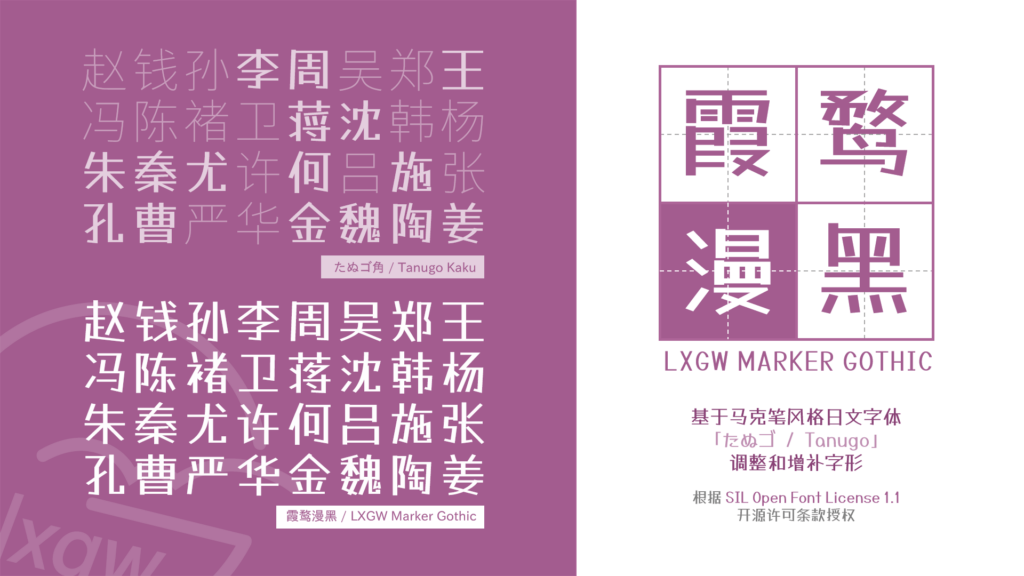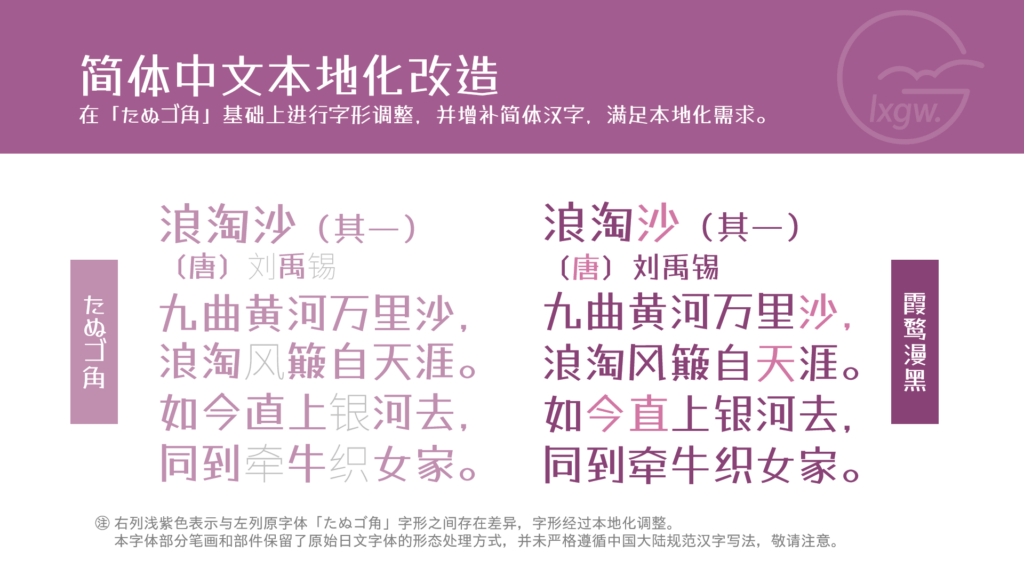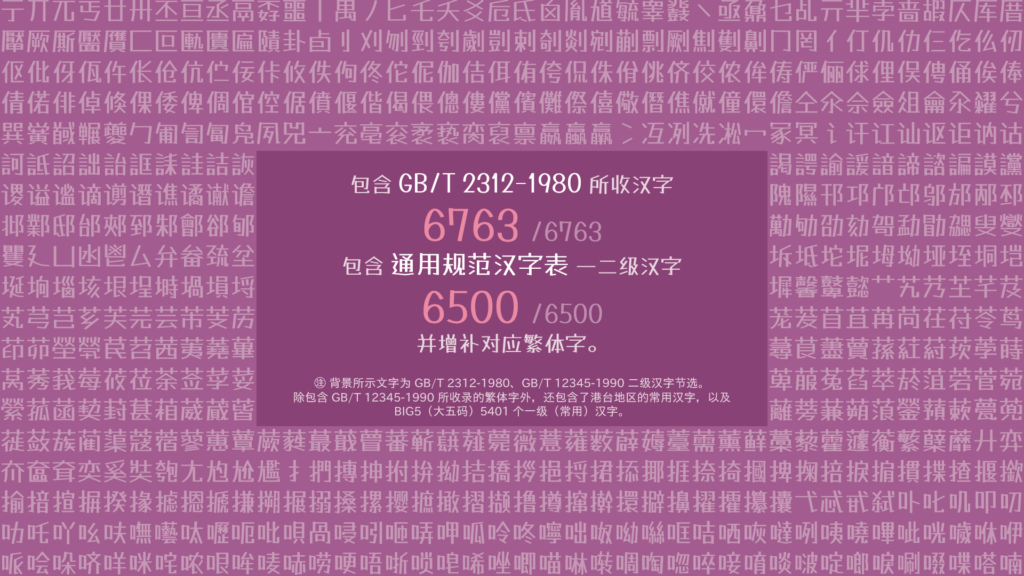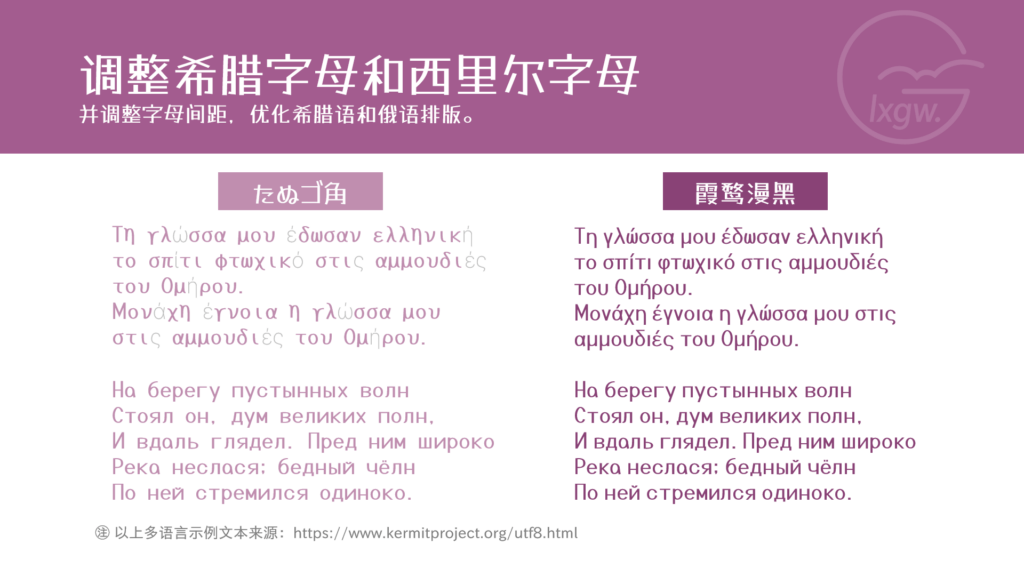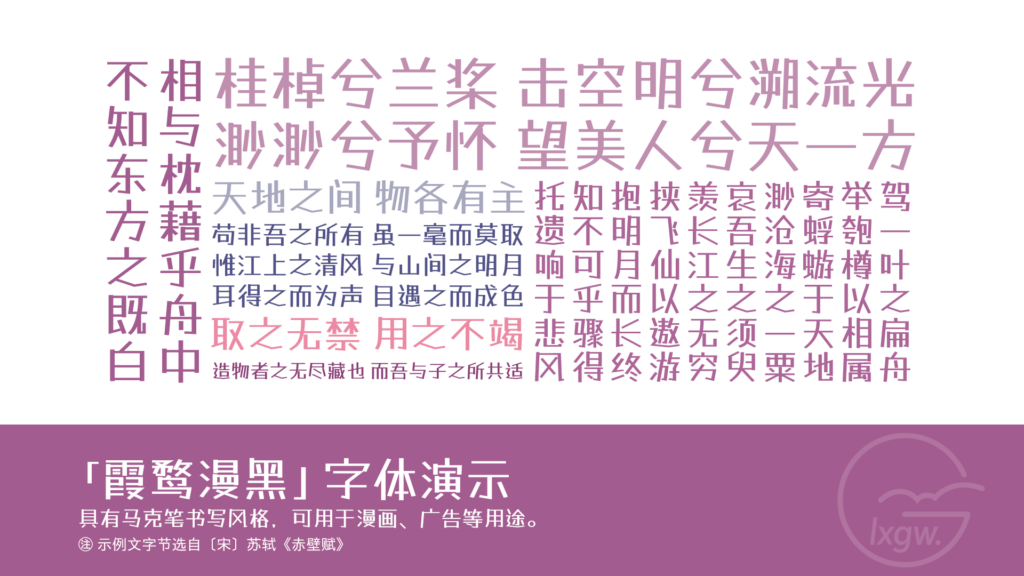
霞鹜漫黑 一款由 Tanugo 衍生的开源中文字体。
本字体基于经典日文字体Tanugo进行深度改造,专门设计为具有鲜明马克笔书写风格的中文字体。在保留原字体结构稳定性的同时,其笔画边缘增添了自然的墨迹质感与手绘的微颤效果,模拟出马克笔快速书写时的视觉韵律,非常适合用于漫画对白、动画标题、广告标语以及各类需要突出活泼、随性或手绘风格的设计场景。